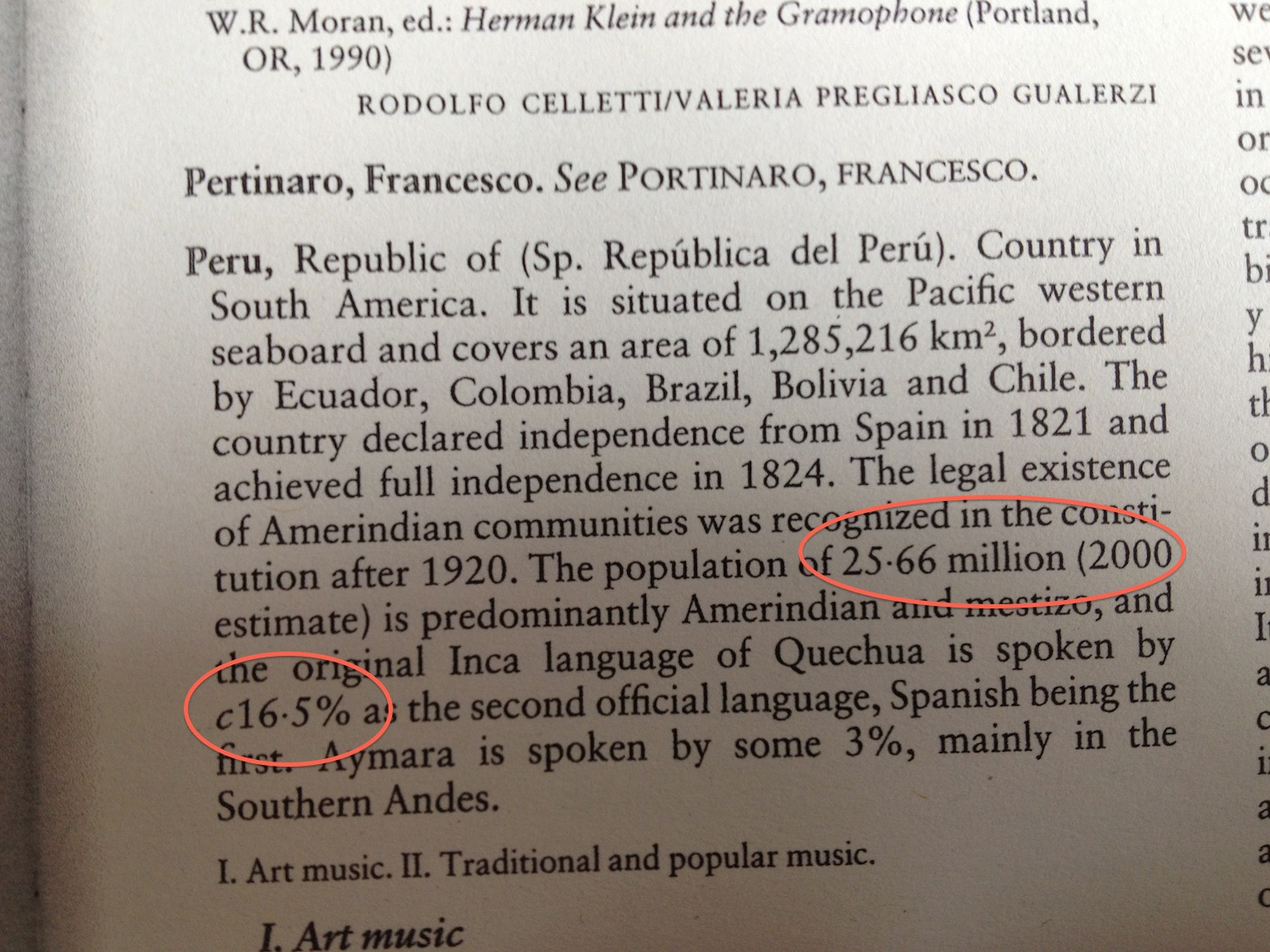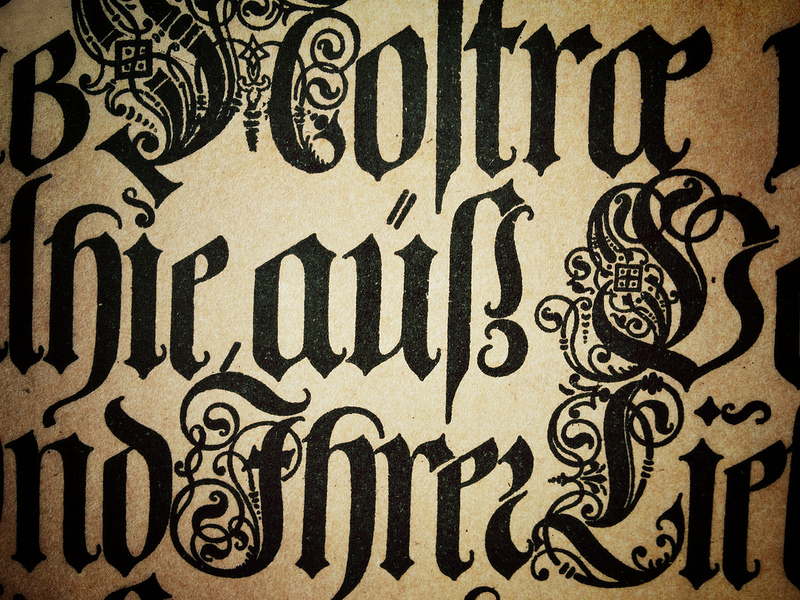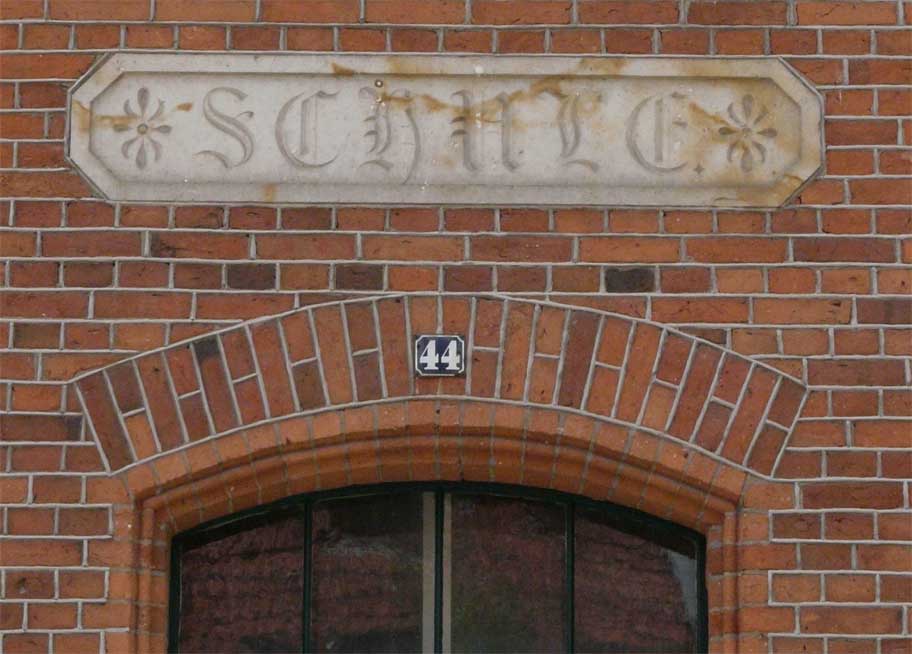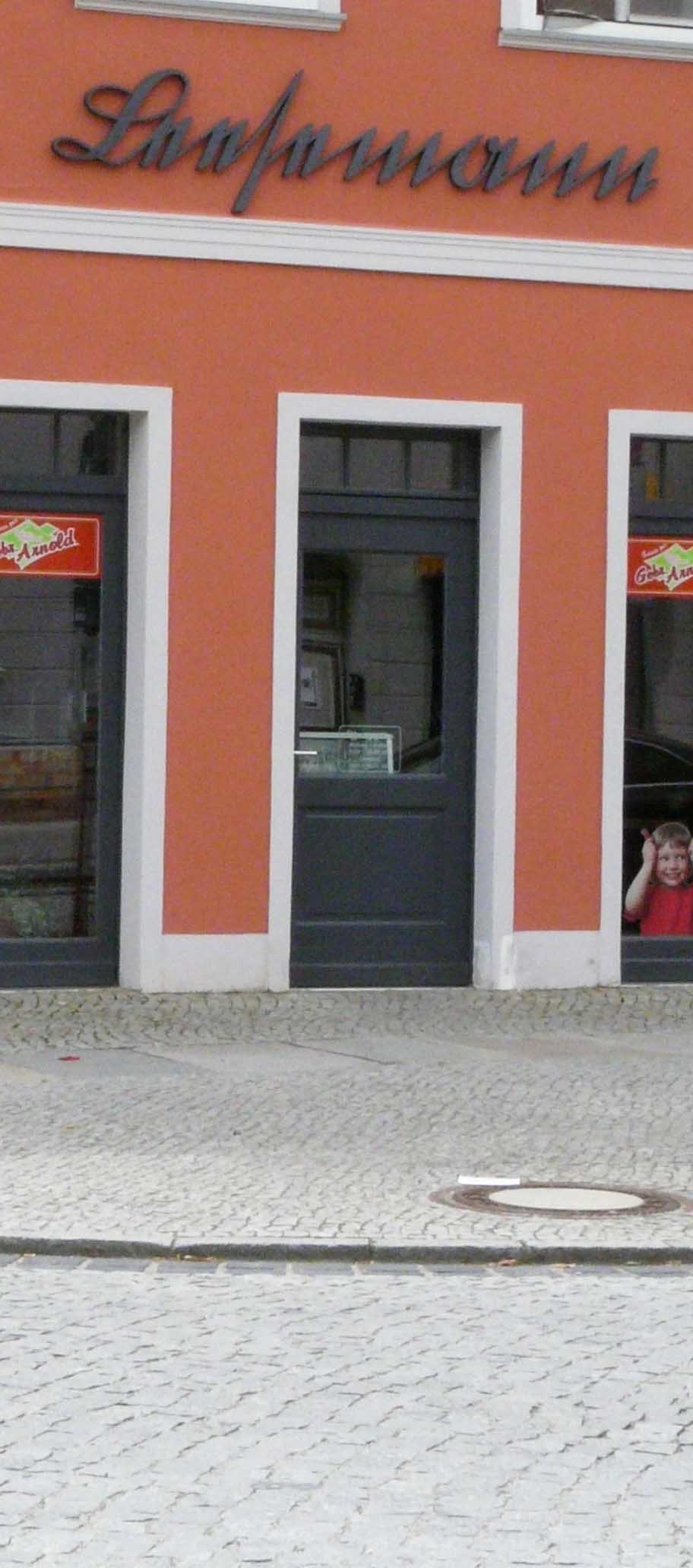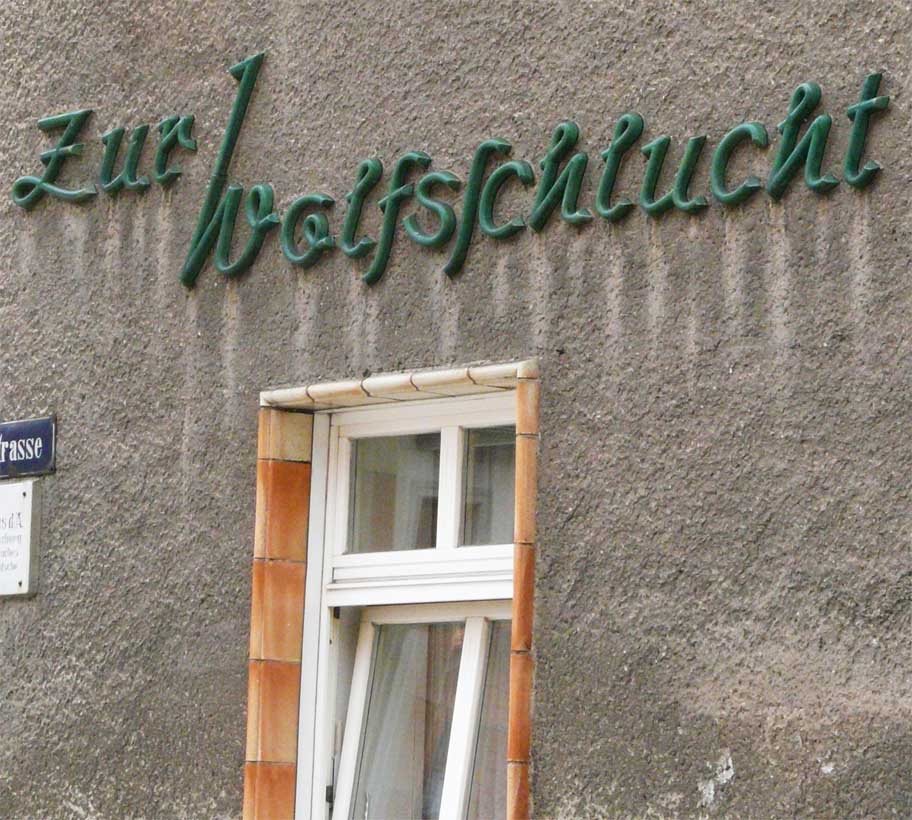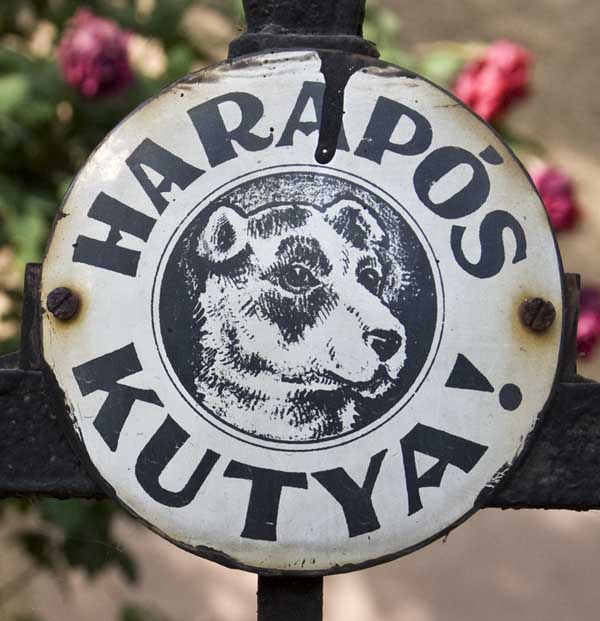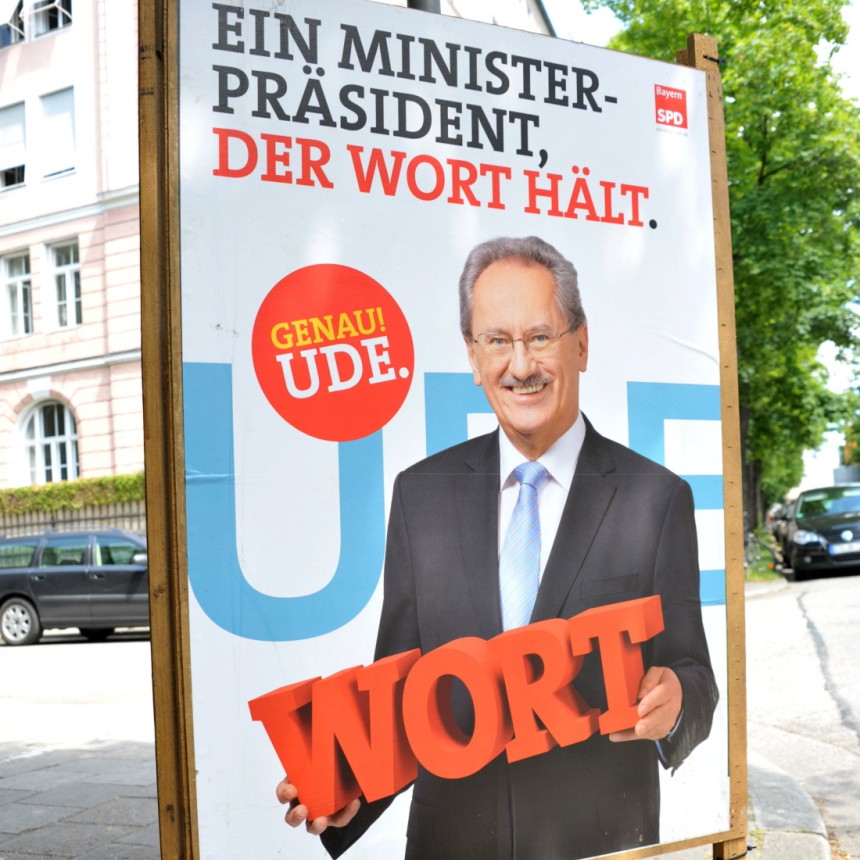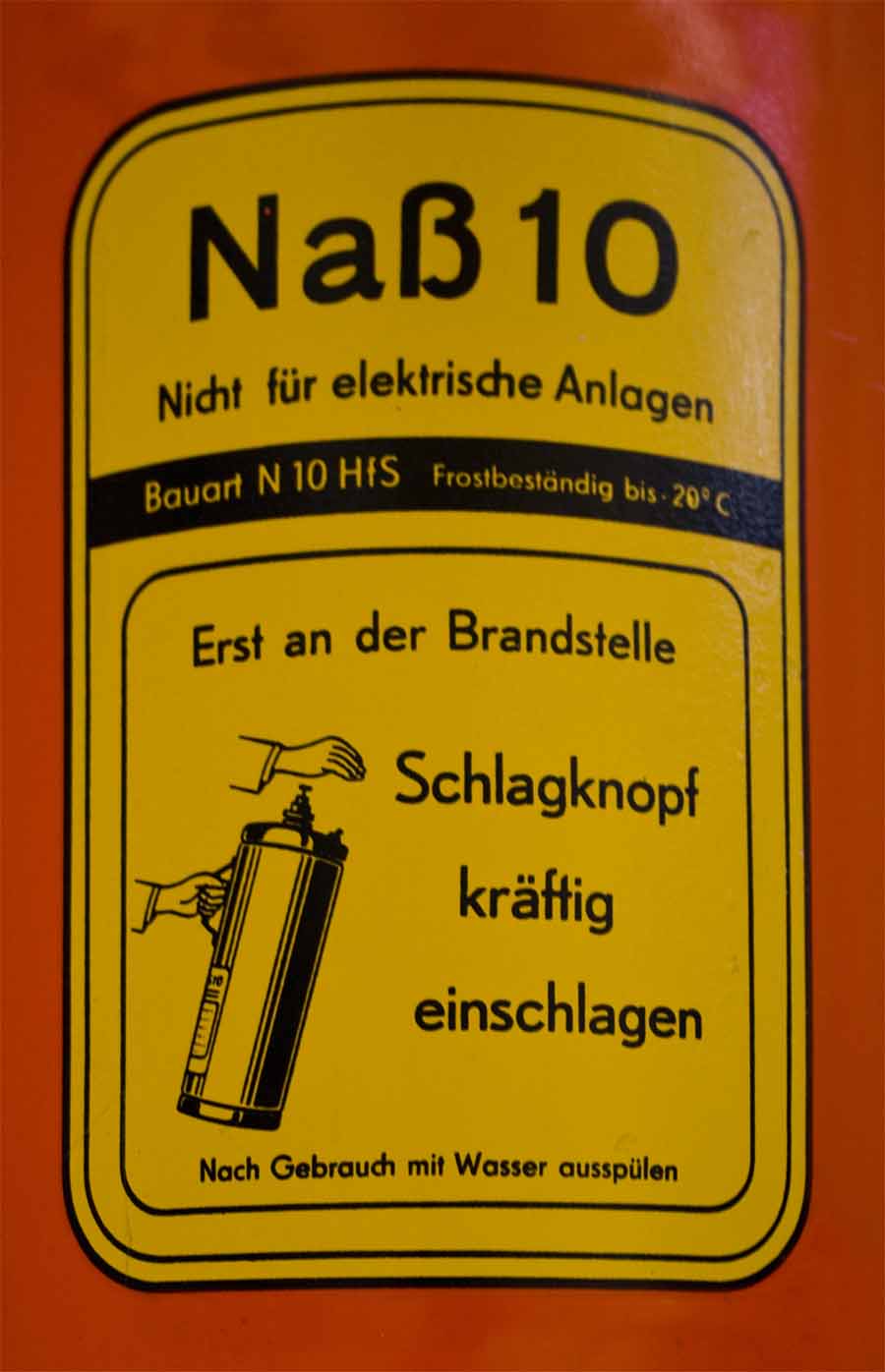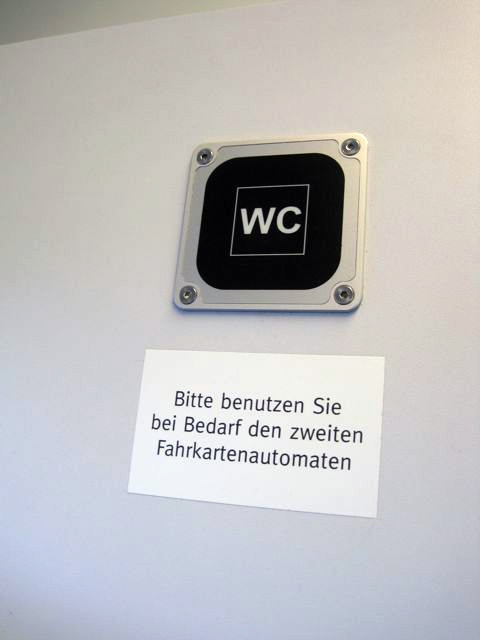
Ein seltsames @-Symbol
Im Kontext:
Gefunden auf der Seite von Alfred (sehr praktischer OSX-Helfer übrigens …)
So’n Quatsch. Der 15. 6. 3012 ist doch gar kein Sonnabend!
Re »negatives« @: Das hat was, finde ich. Solange es eine alternative Form für weniger auffällige Einsätze gibt ...
Ich find’s sehr gewöhnungsbedürftig. Zumal es auf der Seite ja im normalen Fließtext eingesetzt wird (s. meine Ergänzung)
In Bayern wird noch Wort gehalten!
Kindheitserinnerungen:
Kennt eigentlich jemand die Schrift mit diesem witzigen a (also alles, was hier nicht Futura ist)?
Friedliche Koexistenz
in Marburg
:tuschel: Und wann kommt das 3. Schild (mit der Beschriftung »Schlosssteig«)?
Neulich an einem dieser Plastikhäuschen gesehen die immer auf Baustellen oder bei Festivals herumstehen ...
Ds Hochwasser ging. Den Apostroph ließ es da:
Der ist vermutlich sauberer als die meisten Zugtoiletten und insofern vielleicht nicht die schlechteste Alternative. Ist denn um den Automaten auch eine Kabine? :-P
Ich bin grad über einen seltsamen Dezimalpunkt gestolpert
Hab mich dann erstmal gewundert, warum die Zahlen als Produkt angeben werden und war kurz davor das auszurechnen … stammt aus dem New Grove Dictionary of Music and Musicians. Dass die Engländer bei Zahlen den Punkt statt des Kommas verwenden und umgekehrt wusste ich ja, aber ein mittiger Punkt ist mir noch nie begegnet. Hat das von euch schonmal jemand gesehen?
ein mittiger Punkt ist mir noch nie begegnet. Hat das von euch schonmal jemand gesehen?
Ja, aber nur handschriftlich, z.B. auf mit Kreide beschriebenen Schildern vor Gaststätten, Gemüseläden u.ä. Wenn ich mich recht erinnere, aber eher in England als den USA. Wissen unsere Briten mehr?
Schaut mal, ich habe ein neues Lieblingsbuch!
Es heißt »Praktisches Kochbuch. Zuverlässige und selbstgeprüfte Recepte der gewöhnlichen und feineren Küche. Practische Anweisung zur Bereitung von verschiedenartigen Speisen, kalten und warmen Getränken, Gelees, Gefrornem, Backwerken, sowie zum Einmachen und Trocknen von Früchten, mit besonderer Berücksichtigung der Anfängerinnen und angehenden Hausfrauen«
von Henriette Davidis (erstmalig erschienen 1845) und Luise Holle, letztere bearbeitete und aktualisierte die späteren Auflagen des Buches über Jahrzehnte hinweg. Die Auflage, die ich einsehen und abfotografieren durfte, ist die 48. von 1914.
Ich möchte Euch meine Lieblingsseiten nicht vorenthalten: